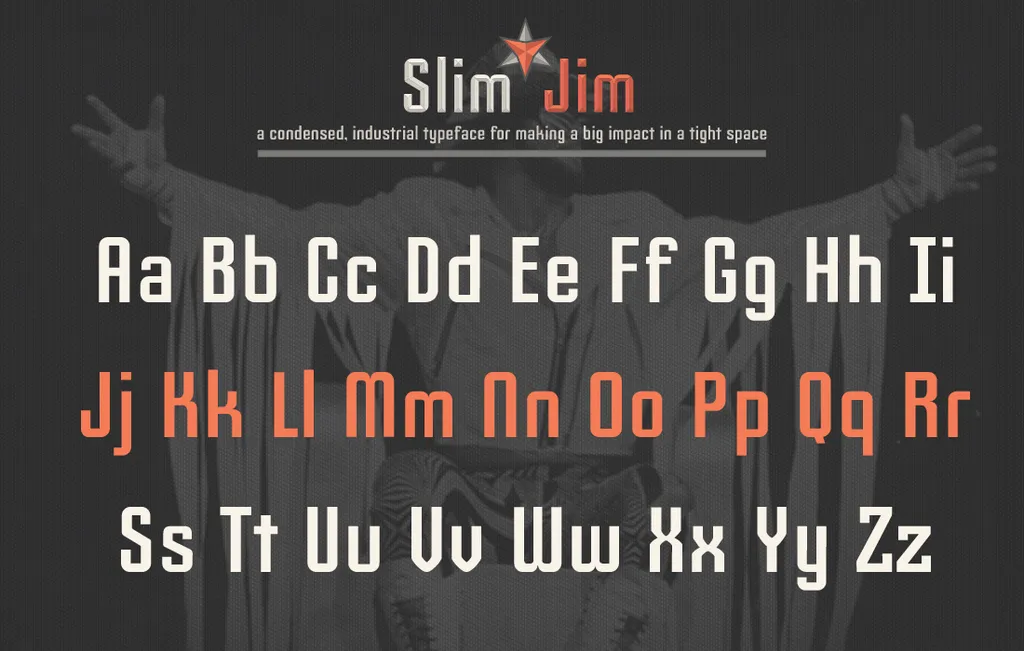
Slim Jim Font
A fonte Slim Jim foi criada por Jeremy Cohen como uma tipografia condensada e industrial perfeitamente adaptável para títulos e subtítulos. Suas linhas finas e espaçadas reduzidas permitem que você use essa fonte de maneira concisa em ambientes visuais mais elaborados, ajudando a destacar textos-chave com estilo único e moderno. Ideal para usar nas seções principais ou no topo de páginas web, Slim Jim é perfeita para quem deseja um toque industrial e clean em seus projetos gráficos. Este é o tipo certo para quando você quer sua informação chamar a atenção imediatamente. A fonte foi desenvolvida pelo designer Hamilton e está disponível na categoria de Fontes Sans Serif, uma escolha perfeita para aqueles que buscam um estilo moderno e minimalista em seus materiais digitais.